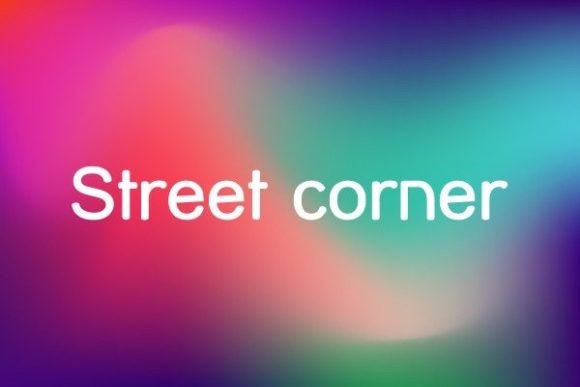
Esquina de calle, fuente urbana para señalización y marca
Street Corner 2 es una fuente de exhibición de estilo manuscrito con letras redondeadas y amigables que aportan a los diseños un toque informal y artesanal. Su estilo informal es ideal para proyectos que necesitan personalidad, calidez o un toque artesanal único, desde pósteres y tarjetas de felicitación hasta productos y branding. Como fuente digital descargable, se integra a la perfección con software de diseño, flujos de trabajo de archivos de corte y configuraciones de impresión bajo demanda.
Esta fuente es ideal para creativos, artesanos, propietarios de pequeñas empresas y diseñadores que desean una tipografía divertida y de aspecto artesanal para productos digitales o físicos.
- Estilo amigable y escrito a mano: brinda a sus diseños una sensación cálida y personal en lugar de un aspecto frío y rígido.
- Listo para exhibir: ideal para encabezados, logotipos y elementos de diseño que necesitan destacarse
| Estilo | Exhibición manuscrita/casual | Sans-serif/serif neutro: encabezados simples o cuerpo de texto | Sans-serif o serif rígidos, personalidad mínima |
| Vibración / Sensación | Amable, artesanal, creativo. | Limpio, neutral, profesional. | Minimalista, moderno y utilitario. |